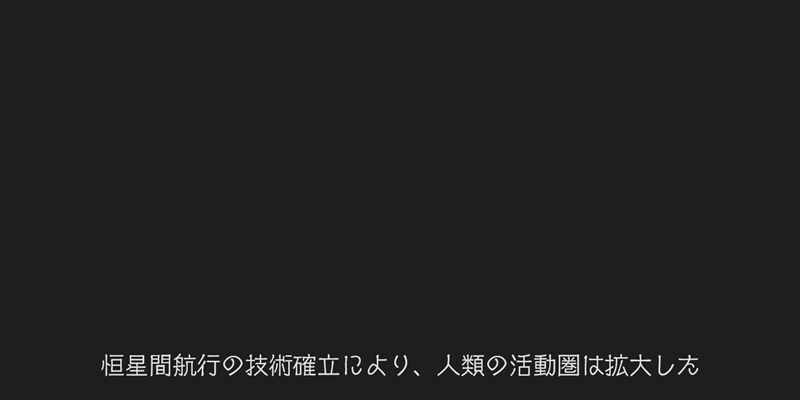
ニューシネマ (ニューシネマA / ニューシネマB) フォントの作例
ニューシネマ (ニューシネマA / ニューシネマB) フォントの作例です。
映画の字幕の文字のデザインのフォントです。
映像の字幕以外に、ゲームのテキストなどでも使われるフォントです。
ニューシネマA の作例です。
ニューシネマ (ニューシネマA / ニューシネマB) フォントの作例:画像1
ニューシネマB の作例です。
ニューシネマ (ニューシネマA / ニューシネマB) フォントの作例:画像2
ニューシネマBは漢字が省略体になっていることが確認できます。「間」の文字がわかりやすいです。
また、ニューシネマBでは“空気穴あき”と呼ばれる線がつながらないアクセントがあります。「日」や「口」の部首で左上部分に空きがある箇所などで違いが判ります。